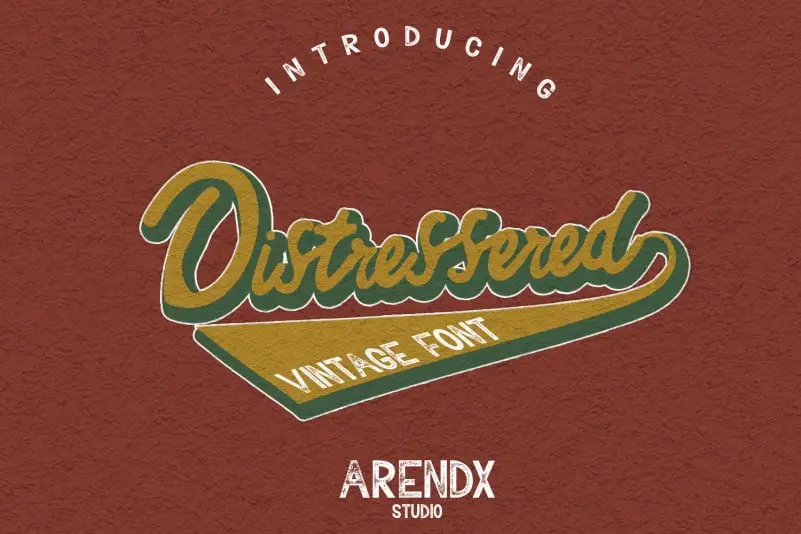
Distressered Vintage Font – Fonte Grátis
Distressered Vintage Font
A Distressered Vintage Font é uma criação única que oferece uma experiência de escrita agridoce para designers e criadores de conteúdo no Brasil. Criada inspirada nas letras manuscritas, esta fonte monoline apresenta um estilo vintage elegante com muitos recursos únicos como alternativas estilizadas e swashes. Os usuários encontrarão esta fonte em formatos OTF, TTF e WOFF para maximizar a versatilidade de uso. Se você está procurando por uma fonte que oferece uma mistura entre o clássico e o moderno, a Distressered Vintage Font é um verdadeiro prêmio. Não há necessidade de instalar software especializado; basta seguir o procedimento tradicional de instalação para começar a usar esta fantástica fonte em seu próximo projeto. Uma fonte que se adapta à sua criatividade, sem abrir mão do aspecto vintage que ela traz.